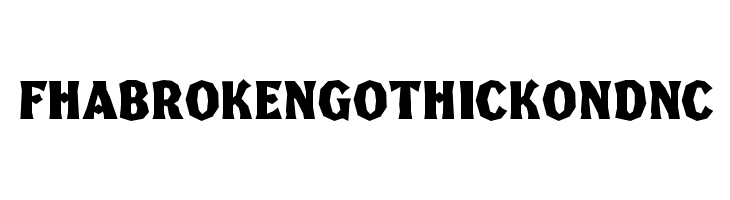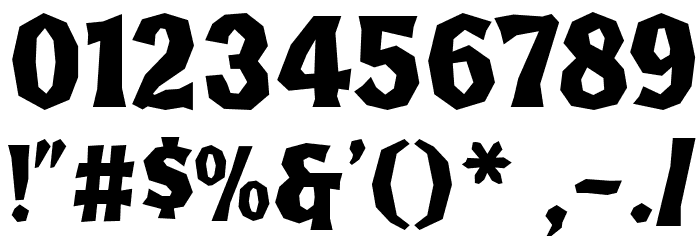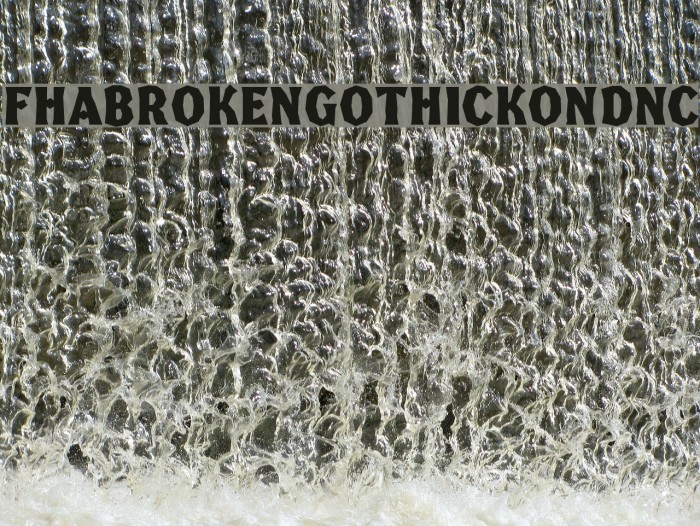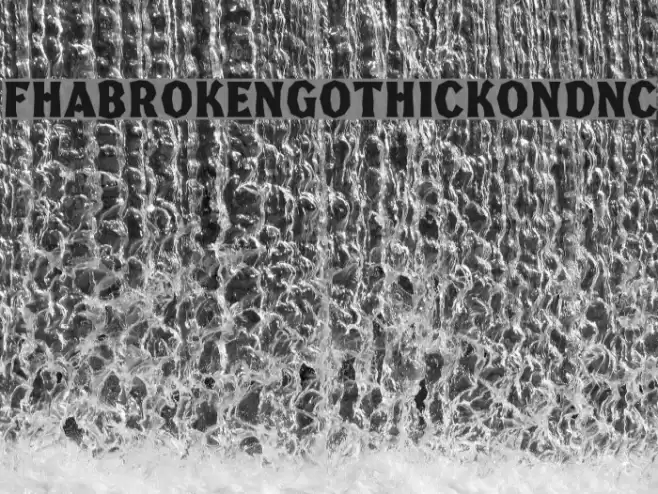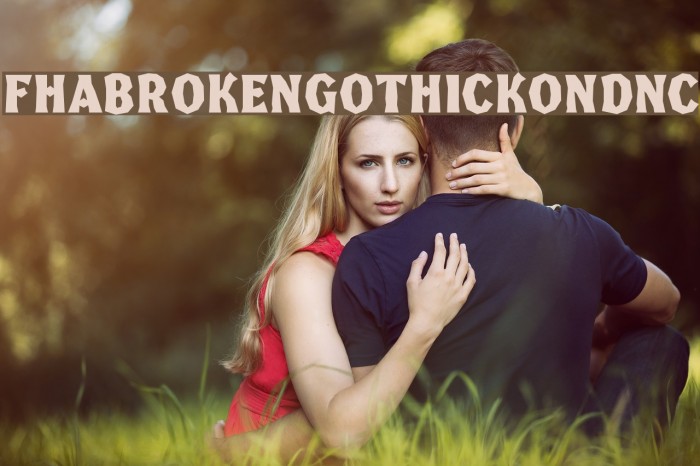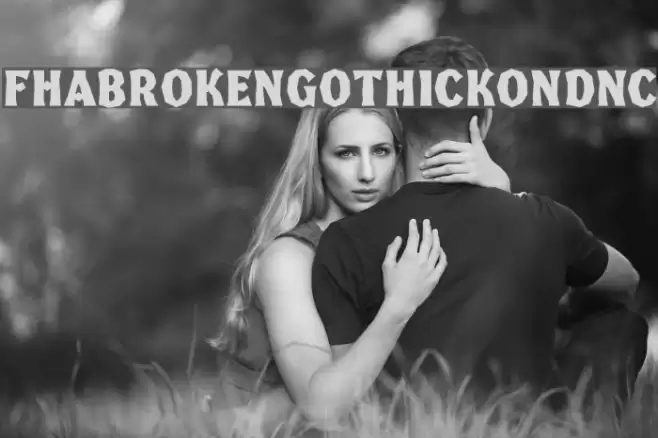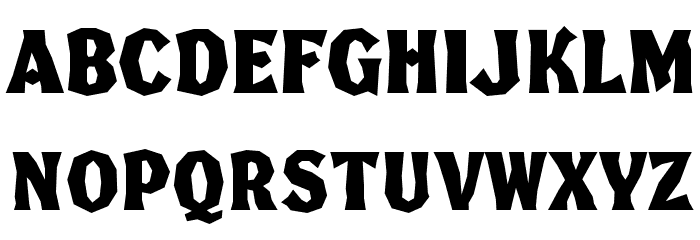
FHABrokenGothicKondNC Font
✎ Gothic
| Categorías | Gothic |
| Estilo general | Gothic, Edgy, Bold |
| Proyectos propuestos | Ideal for posters, album covers, branding for edgy or alternative products, and any design needing a strong, gothic touch. |